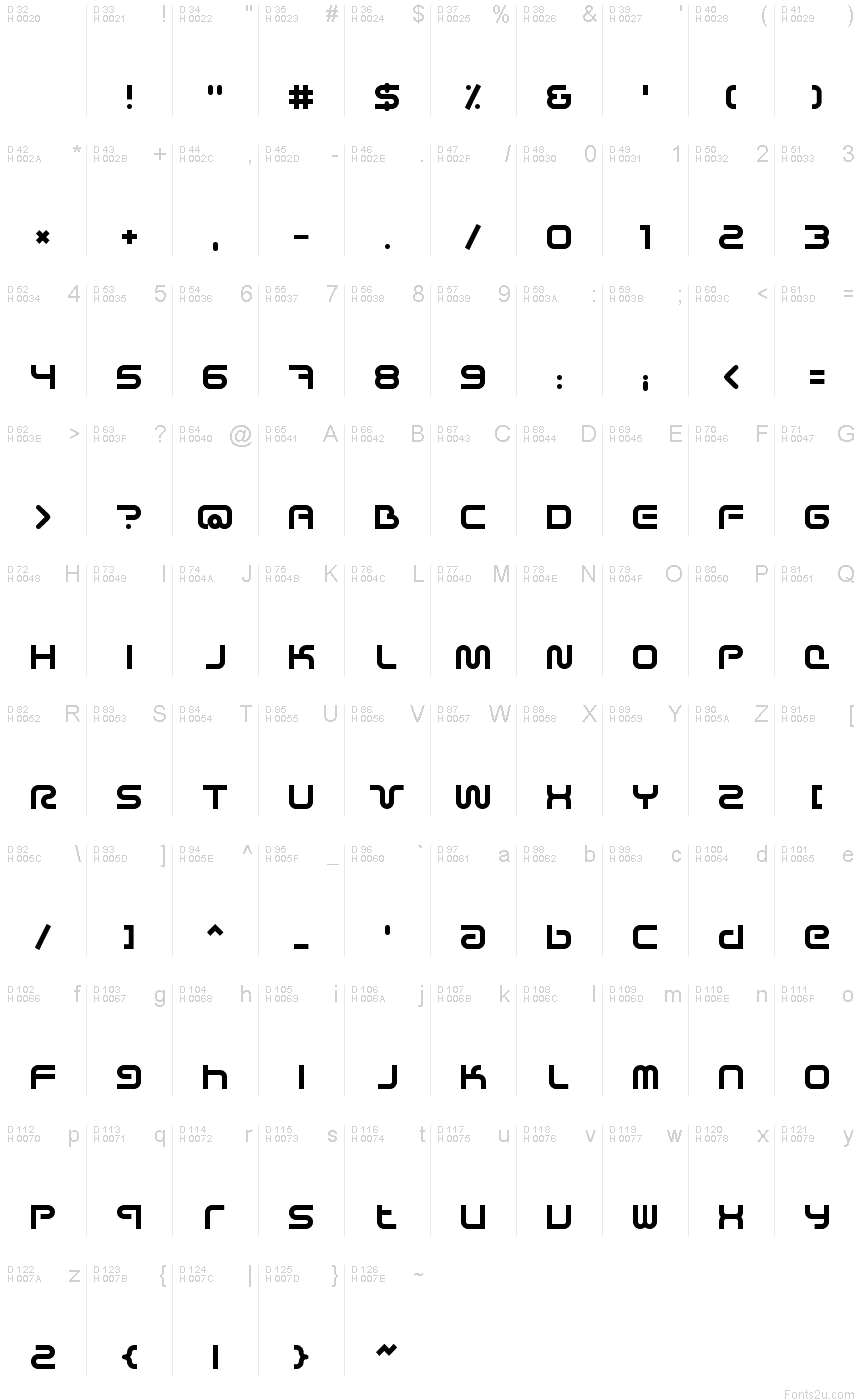
Sci Fied X, un font display futuristico e gratuito di dustBUST Fonts, si ispira direttamente all'immaginario sci-fi di fine anni '90, con maiuscole composte da canali spessi e arrotondati con intagli quadrati. Le lettere hanno un aspetto compatto e ingegneristico, ma gli angoli ammorbiditi evitano che risultino fredde, donando al font un carattere elegante da sala giochi o pannello di controllo.
È la scelta naturale e gratuita per loghi di videogiochi, titoli di poster, eventi tech, copertine musicali e title card in cui una parola breve deve trasmettere un impulso sintetico. Si adatta bene anche al branding di gadget o alla grafica per streaming, poiché le maiuscole richiamano una segnaletica modulare piuttosto che una semplice scrittura geometrica.
Sci Fied X